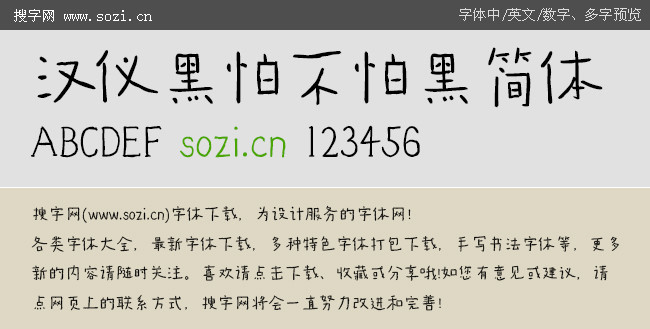
漢儀黑怕不怕黑簡體
搜字網(wǎng)給大家提供一款漢儀黑怕不怕黑簡體中文字體下載,漢儀黑怕不怕黑簡體是一款手寫風(fēng)格的卡通字體。字跡扁長而清瘦,書寫隨性灑脫。適用于兒童畫冊設(shè)計(jì)、卡通海報(bào)設(shè)計(jì)、包裝設(shè)計(jì)等場合使用。(本字體為個(gè)人非商用版,如需要商用請聯(lián)系漢儀公司購買版權(quán))